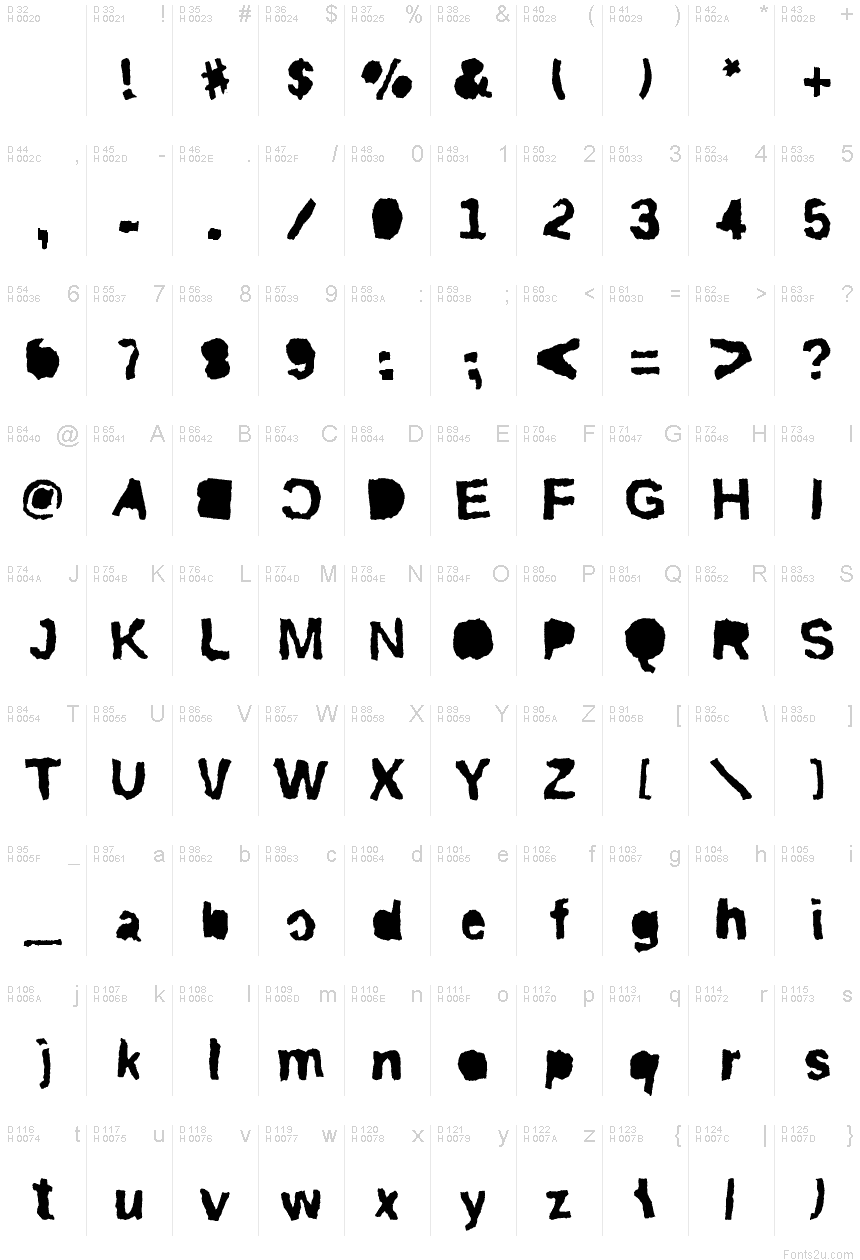
ripTRASH Mirror autorstwa Manuela Viergutza to darmowy, nadgryziony zębem czasu krój displayowy, zbudowany z szerokich, tępych, postrzępionych liter. Ciężkie, nieregularne pociągnięcia przypominają kształty wycięte zgrubnie z poniszczonego papieru.
Projektanci działający w kulturze punkowej, deskorolkowej i undergroundowej muzyce uznają go za odpowiedni na okładki albumów, plakaty koncertowe i sitodrukowy merch. Surowa sylwetka nadaje również grafikom imprezowym bezpośrednią siłę ręcznie robionych napisów protestacyjnych. Jest szczególnie przekonujący w tematach związanych z noise'em, buntem, sztuką uliczną i wydawnictwami niezależnymi (DIY).
„rip TRASH” zawiera 6 stylów: regular, mirror, cut, cutMIRROR, round i roundMIRROR, z 100 glifami, w tym znakami akcentowanymi.